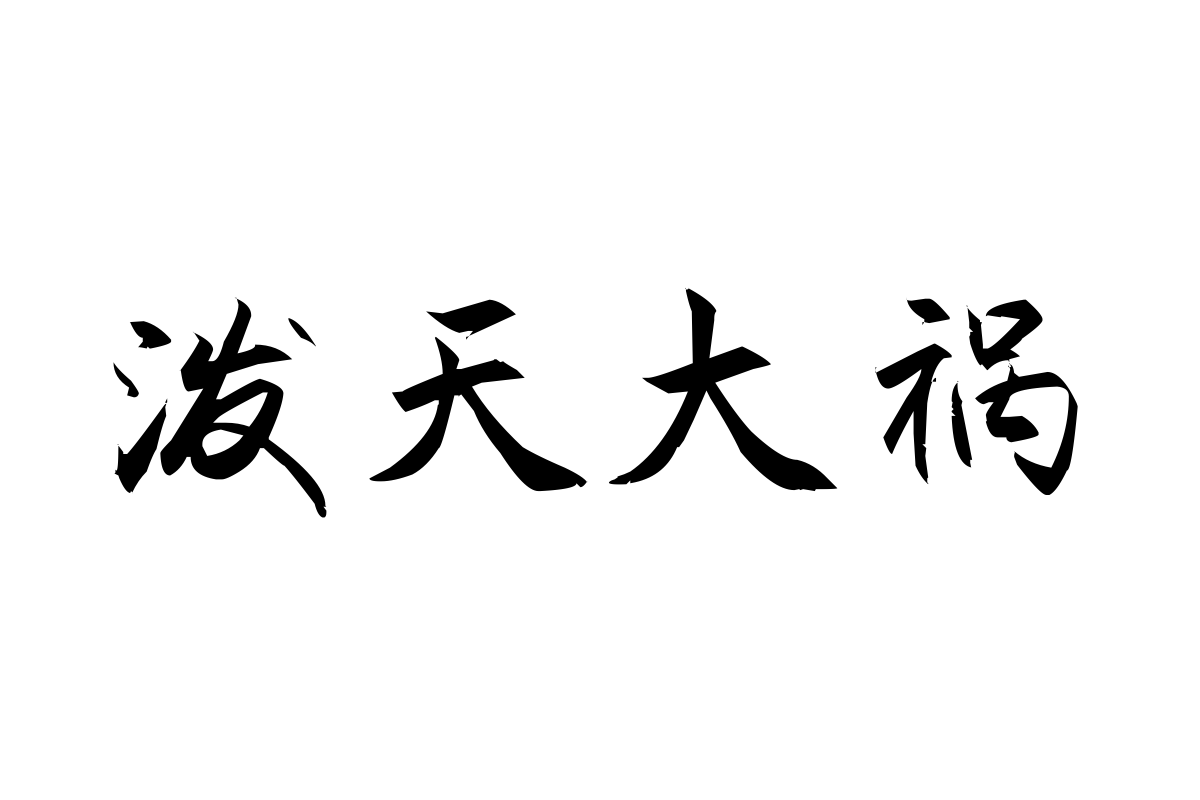
米开飘逸行楷减细版是一款由米开设计工作室开发的中文书法字体,具有独特的风格和特点。这款字体采用了行书的书写方式,笔画流畅自然,线条粗细适中,给人一种优雅而流畅的感觉。同时,字体结构紧凑,字间距均匀,使得整个字形看起来更加美观大方。
米开飘逸行楷减细版在细节上进行了优化,将笔画进行了细化处理,使字体更加精致。同时,字体中的一些细节部分也进行了简化,使得整体视觉效果更加简洁明了。此外,这款字体还保留了一些传统的书法元素,如横画、竖画等,使得字体既有现代感又不失传统韵味。